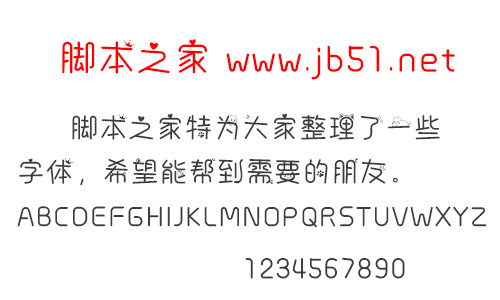
字心坊貓小鎮(zhèn)體是字心坊字庫推出的一款非??蓯鄣膫€性藝術(shù)字體,該字體加入了大量的貓可愛元素,整體風(fēng)格文藝、新穎、可愛、卡通、小清新,非常適合廣告設(shè)計、字體設(shè)計等相關(guān)領(lǐng)域,歡迎喜歡字心坊貓小鎮(zhèn)體的朋友前來下載使用。